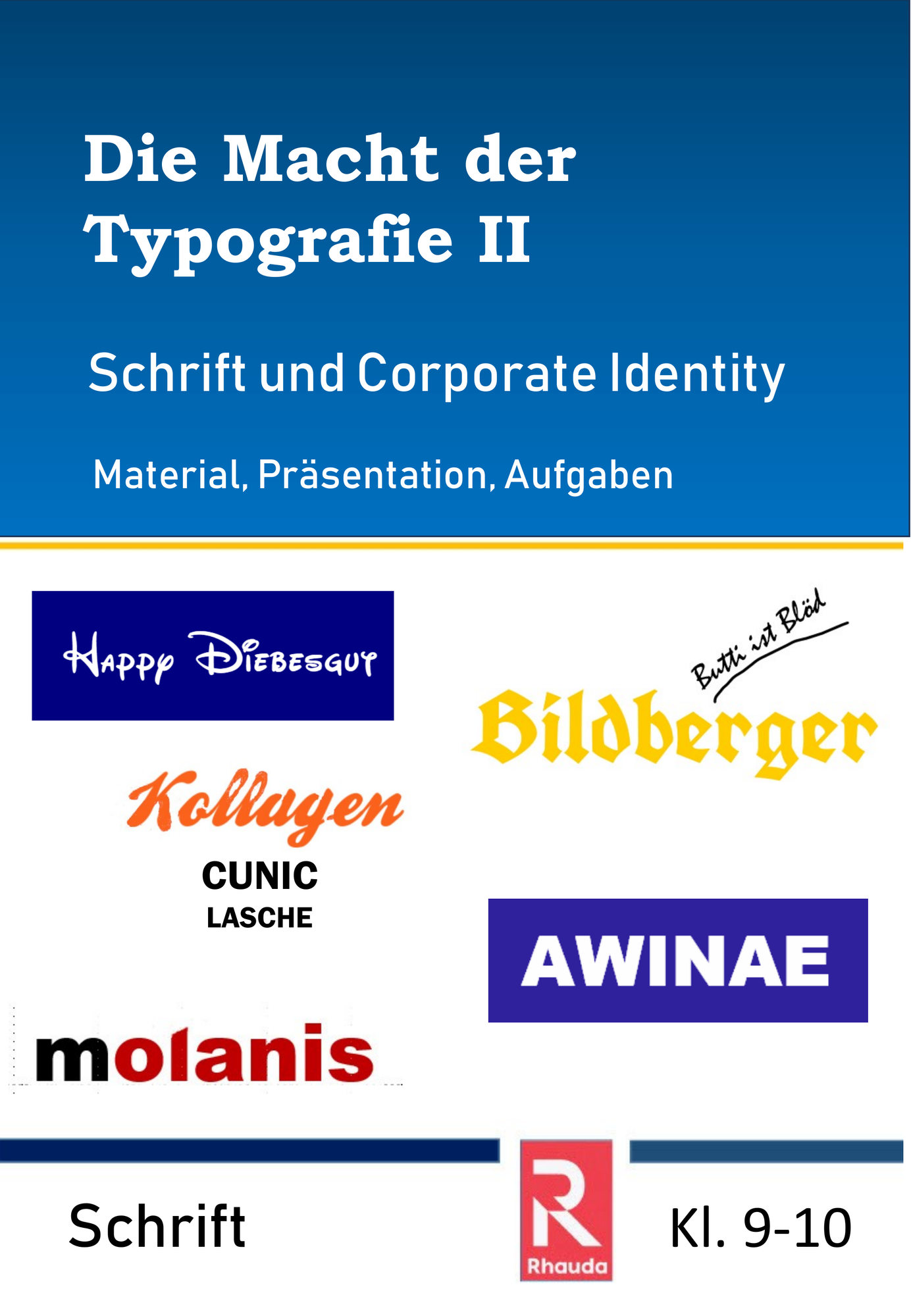
Du möchtest deinen Schüler*innen die faszinierende Welt der Typografie näherbringen? ! Tauche ein in die Macht der Schriften und entdecke, wie sie Produkte und Unternehmen prägen. Deine Schüler*innen lernen, wie Schriftarten Emotionen wecken und Botschaften verstärken.
Was dich in diesem Material erwartet:
• Eine umfassende Präsentation, die die Grundlagen der Typografie einfach erklärt.
• Detaillierte Einblicke in verschiedene Schrifttypen: von klassischen Serifen- und serifenlosen Schriften über markante Slab-Serif- und elegante Script-Fonts bis hin zu dekorativen und gebrochenen Schriften.
• Mit Aufgabenkarten die Möglichkeit, die Schrifttypen per Gruppenarbeit untersuchen zu lassen .
• Spannende Aufgaben zur Logo-Analyse, bei denen deine Schüler*innen die Schriftwahl bekannter Marken untersuchen.
• Eine kreative Herausforderung: Entwerft ein eigenes „Mini“-Corporate Design für ein fiktives Produkt.
• Praktische Tipps für die Umsetzung am Computer, um Logos und Texte zu gestalten.
• Lösungsvorschläge und nützliche Links zu den Original-Logos, die die Recherche erleichtern. (Diese Logos können händisch eingefügt werden).
Deine Schüler*innen lernen mit diesem Material:
• Die verschiedenen Schrifttypen und ihre einzigartigen Merkmale zu unterscheiden.
• Die Wirkung von Schriften zu erkennen und zu verstehen, wie sie Botschaften beeinflussen.
• Wie Schriftarten eine Corporate Identity formen und unterstützen.
• Kollaboratives Arbeiten beim gemeinsamen Suchen von Logotypen.
• Kreative Fähigkeiten beim Entwurf eines Logos und eines Mini-Corporate Designs anzuwenden.
• Ihre Schriftwahl bewusst zu begründen und ihre Designentscheidungen zu präsentieren.
Die Macht der Typografie II - Schrift und Corporate Identity